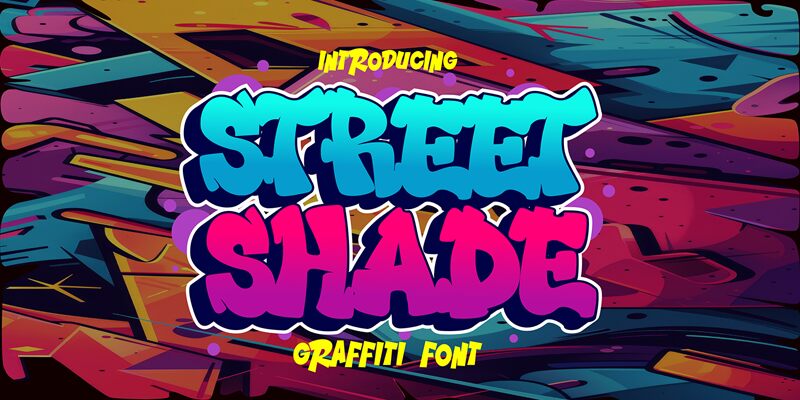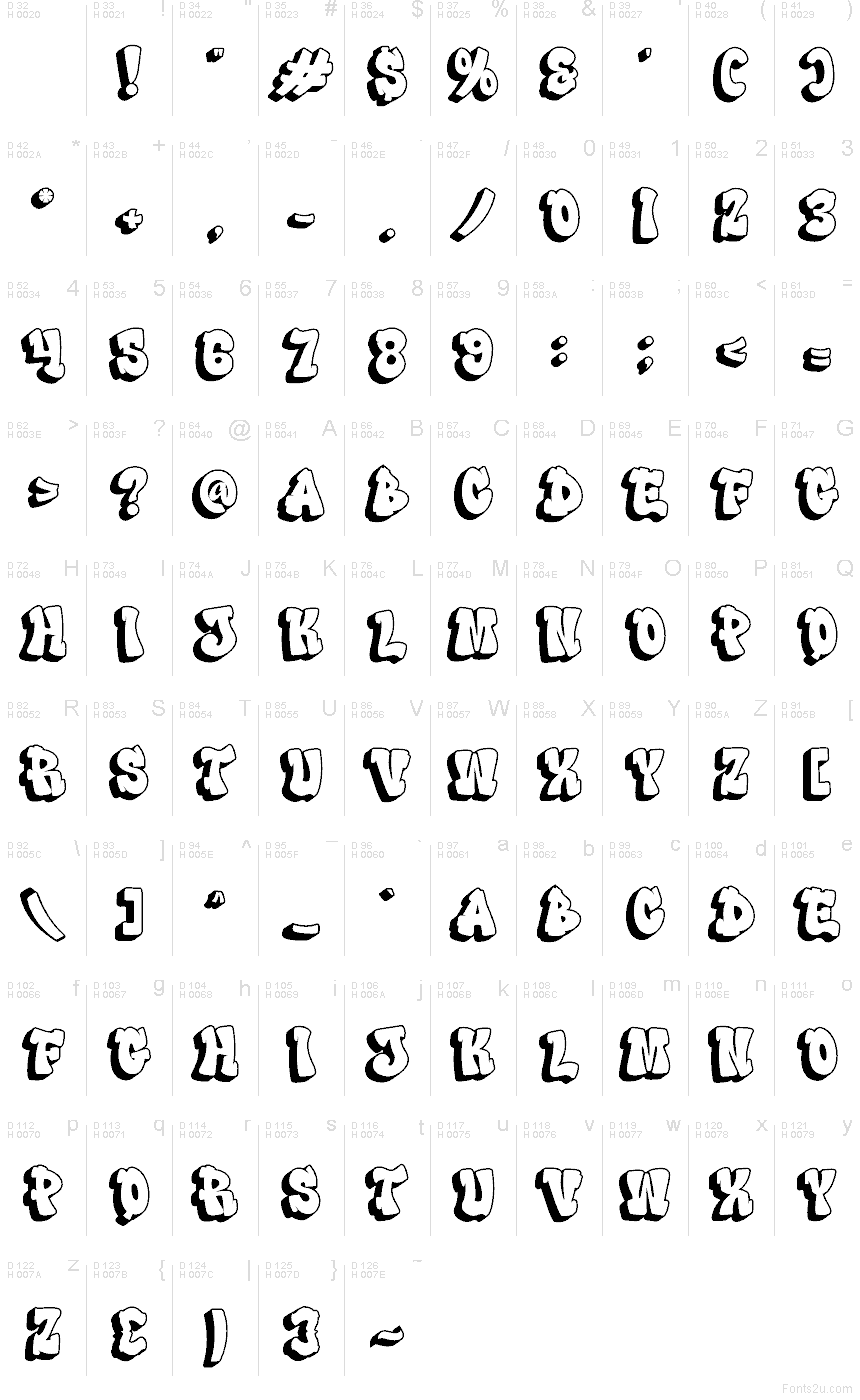
Street Shade-Shadow, creata da Saepul milah di CikareotypeStudio x figureeStudio, è un font graffiti gratuito. Con le sue lettere corpose e morbide, quasi aerografate, aggiunge una profondità urbana istantanea a ogni parola grazie a un'ombra decisa. La spaziatura ridotta mantiene il ritmo compatto, facendo in modo che i titoli vengano percepiti come un'unica tag e non come caratteri isolati.
Utilizza Street Shade-Shadow per dare impatto immediato a loghi skate e streetwear, titoli di poster, flyer musicali, miniature YouTube, sticker, banner per eventi e cover di album o mixtape. Questo font gratuito funziona alla grande anche sul packaging, quando cerchi un tocco urbano e giocoso senza rinunciare alla leggibilità. Abbinalo a una sans serif condensata pulita per i dettagli e lascia al font un po' di respiro affinché l'ombra possa sprigionare la sua forza.